Typografie in Offenbach ist nicht nur Koch, Klingspor Museum und HfG. Auch im Alltag finden sich typografisch interessante Fundstücke, vor allem an Hand älterer Beschriftungen. Und überall, wo ich ein altes Schild, Leuchtstoffröhren-Displays, Beschriftungen von Schildermalern sehe, muss ich sie fotografieren.
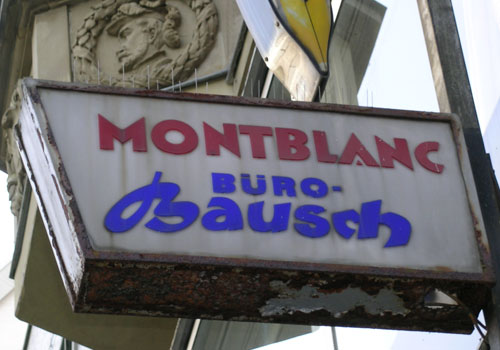
Altes Schild von Büro Bausch in der Waldstraße
Man weiß ja nicht wann diese Schilder durch den Einheitsbrei aus Comic, Serpentine, Arial oder Hobo demnächst ersetzt werden. Die Gründe für das noch existieren dieser Schilder sind ja nicht typografische Überlegungen der Haus- bzw. Ladenbesitzer, sondern finanzielle Einsparungsnotwendigkeiten erlauben es diesen Schildern noch zu existieren. Oder manchmal hat man sie einfach vergessen.
Diese Schilder sind sicherlich nichts einmaliges für Offenbach, aber sie gehören mit dazu und sie sind ein Teil typografischer Entwicklung der letzten Jahrzehnte:
Leuchtstoffröhren-Schilder
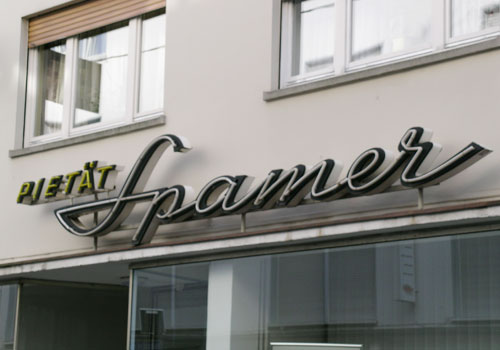
Beerdigungsinstitut in der Großen Marktstraße
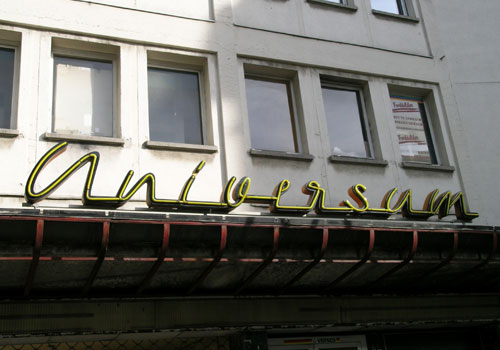
Leerstehendes altes Kino in der Kaiserstraße
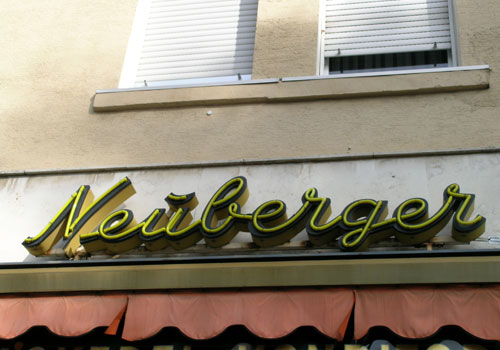
Bäckerei Neuberger in der Ludwigstraße
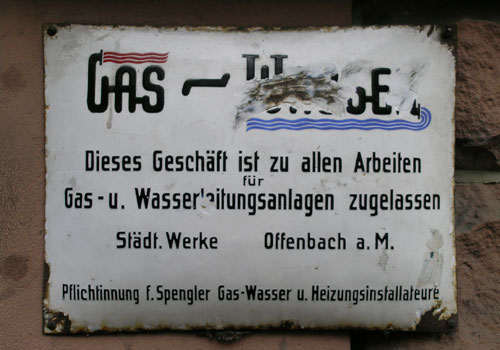
Leider schon etwas zerstörtes Schild in der Bettinastraße
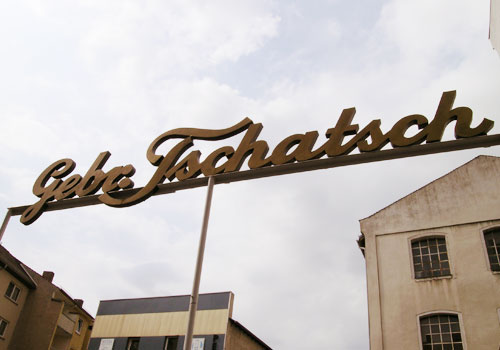
Schriftzug der Firma Gebrüber Tschatsch in der Bernardstraße
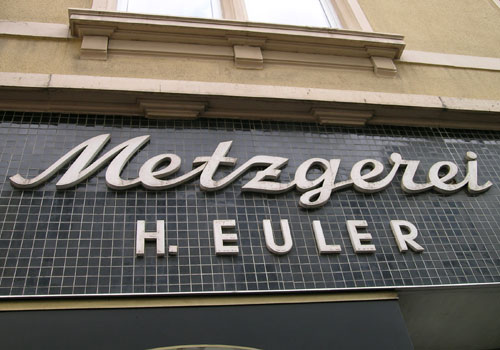
Leerstehendes Ladengeschäft der ehemaligen Metzgerei Euler in der Bernardstraße